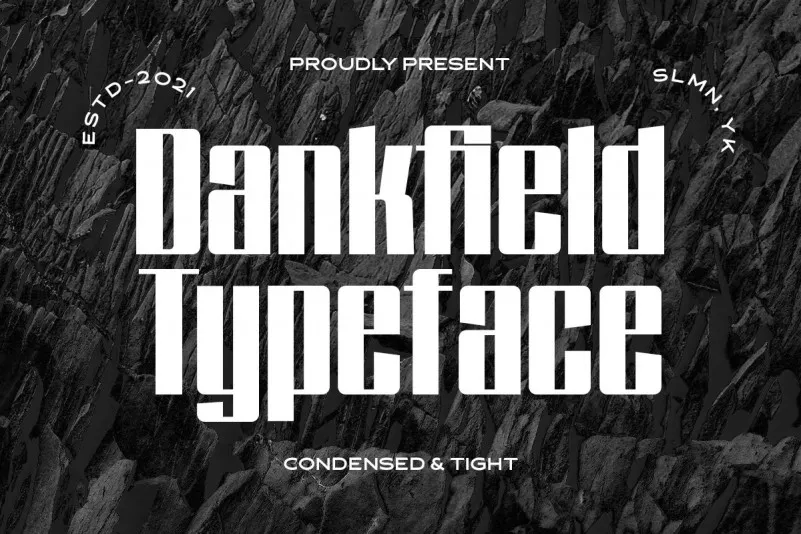
Dankfield Font – Download Grátis
A Dankfield Font é uma escolha perfeita para quem busca elegância simplificada e modernidade geométrica. Desenvolvida com linhas precisas e blocos retangulares, ela pode ser usada em diversas situações, desde logotipos até cartões de festa ou embalagens fashion. Suas formas geométricas fortes combinam perfeitamente com um estilo moderno e clean que torna esta fonte uma opção ótima para qualquer aplicação formal. Seja num evento especial como casamento, em uma revista ou em uma capa de livro, ela proporcionará o equilíbrio perfeito entre simplicidade e destaque. Essa é a fonte ideal para aqueles que buscam um design único e contemporâneo para seus materiais gráficos.